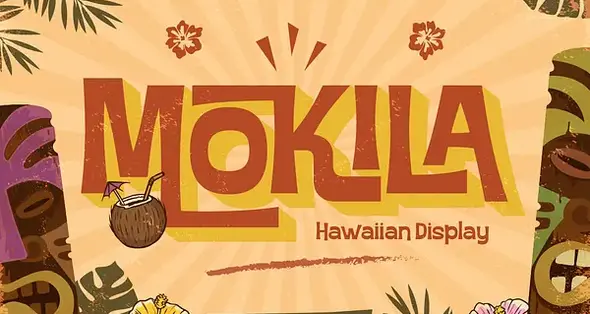
Mokila یک تایپ‌فیس نمایشی هاواییایی جذاب است که برای بخشیدن حسی پرجنب‌وجوش، عجیب و شاد به پروژه‌های خلاقانه شما طراحی شده است! Mokila با ترکیبی بی‌نقص از جذابیت جزیره‌ای و حضوری قدرتمند، به فونت استوایی مورد علاقه شما برای هر طرحی که به ذره‌ای از بهشت نیاز دارد، تبدیل خواهد شد.
Mokila در دو استایل کاربردی عرضه می‌شود: Regular و Extrude. هر دو استایل دارای فرم حروف قوی و درشت هستند که توجه را به خود جلب کرده و خوانایی عالی را تضمین می‌کنند. در حالی که استایل Regular حسی یکپارچه و کلاسیک ارائه می‌دهد، استایل Extrude عمق سه‌بعدی (3D) فوق‌العاده‌ای به متن شما اضافه می‌کند و باعث می‌شود متن شما با لایه‌ای اضافی از سرگرمی و ماجراجویی برجسته شود. طراحی تنومند آن به طور ظریفی داستان‌های کاوش در جزیره و ماجراهای آفتابی را تداعی می‌کند! Mokila برای کارت‌های دعوت مهمانی، برندینگ استراحتگاه‌ها، تبلیغات آژانس‌های مسافرتی، منوی رستوران‌ها، تابلوهای بار یا برندینگ کافه‌ها، پوسترها، تیترها، بسته‌بندی محصولات، لوگوها، فروشگاه‌های لوازم موج‌سواری، استیکرها و موارد مشابه مناسب است.
• حروف بزرگ و کوچک
• اعداد
• علائم نگارشی
• کاراکترهای جایگزین (Alternate)
• لیگچرها (Ligatures)
• چندزبانه
Say "aloha" to Mokila, a captivating Hawaiian display typeface designed to bring vibrant, exotic, and joyful vibes to your creative projects! Perfectly blending island charm with a bold presence, Mokila is set to become your favorite tropical font for any design needing a splash of paradise.
Mokila comes in two versatile styles: Regular and Extrude. Both styles feature strong, chunky letterforms that command attention and ensure excellent readability. While the Regular style offers a solid, classic feel, the Extrude style adds a fantastic 3D depth, making your text pop with an extra layer of fun and adventure. There's just something about its robust design that subtly whispers tales of island exploration and sunny escapades! Mokila good for party invitations, resort branding, travel agency promotions, restaurant menus, bar signage, or café branding, posters, headlines, product packaging, logos, surf shop, stickers and so on.
Uppercase & Lowercase
Number
Punctuation
Alternate
Ligatures
Multilingual